با سلام در این مقاله از وب سایت فونت زیبا قصد داریم به شما نحوه افزودن فونت به اینشات رو آموزش بدیم . نرم افزار اینشات inshot به صورت پیش فرض از فونت های سیستمی لاتین که بدون جذابیت لازم هستند استفاده می کنه . اینشات با رابط کاربری آسونی که داره طرفداران و استفاده کنندگان زیادی داره و کاربران به دنبال خلق تولید محتواهای زیبا و خفن و منحصر به فرد هستند.
یکی از مهم ترین عوامل در افزایش جذابیت و زیبای بصری تولید و محتوا ها به طور قطع انتخاب فونت و تایپ فیس زیبا و به روز است. امروزه به همت تلاش طراحان تایپوگرافی فارسی فونت های بسیار زیبایی در دسته بندی ها و کاربرد های مختلف ساخته و ایجاد شده است.
افزودن فونت به نرم افزار اینشات
خب بریم سراغ موضوع اصلی مون خیلی ساده و سریع نحوه افزودن فونت رو به نرم افزار اینشات توی تصاویر زیر به شما دوستان آموزش دادیم. کافیه که پس از دانلود فونت اول بدونید که فونت دانلودی شما در کدام مسیر یا محل گوشی یا کامپیوترتون قرار گرفته. سپس بازدن قسمت متن و باز شدن پنجره اون دکمه بارگیری رو بزنین و به اون مسیری برین که فونتتون انوجا هست و ذخیره شده.
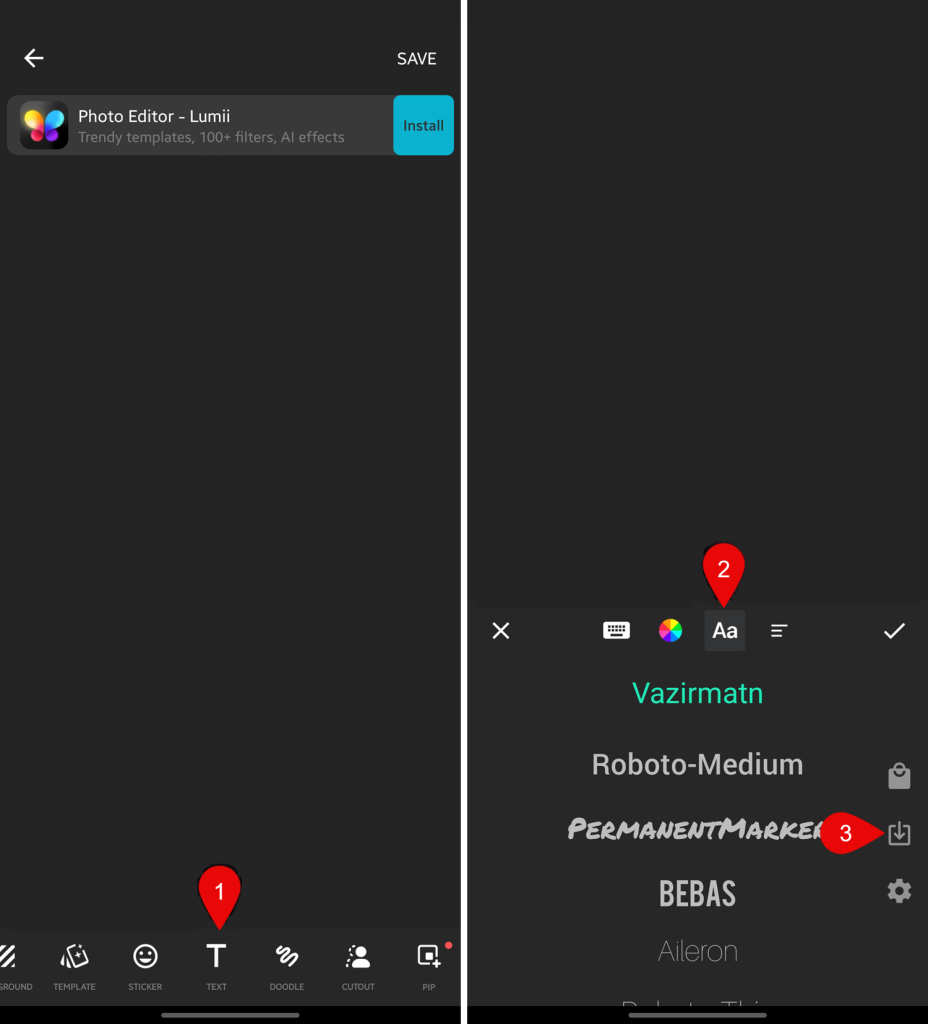
به همین سادگی شما نحوه افزودن فونت به اینشات رو یاد گرفتین. فقط به خاطر داشته باشین برای تایپ فیس هایی که چندین وزن متفاوت رو پشتیبانی می کنند. هر وزن رو باید جداگانه به نرم افزار inshot اضافه کنین .